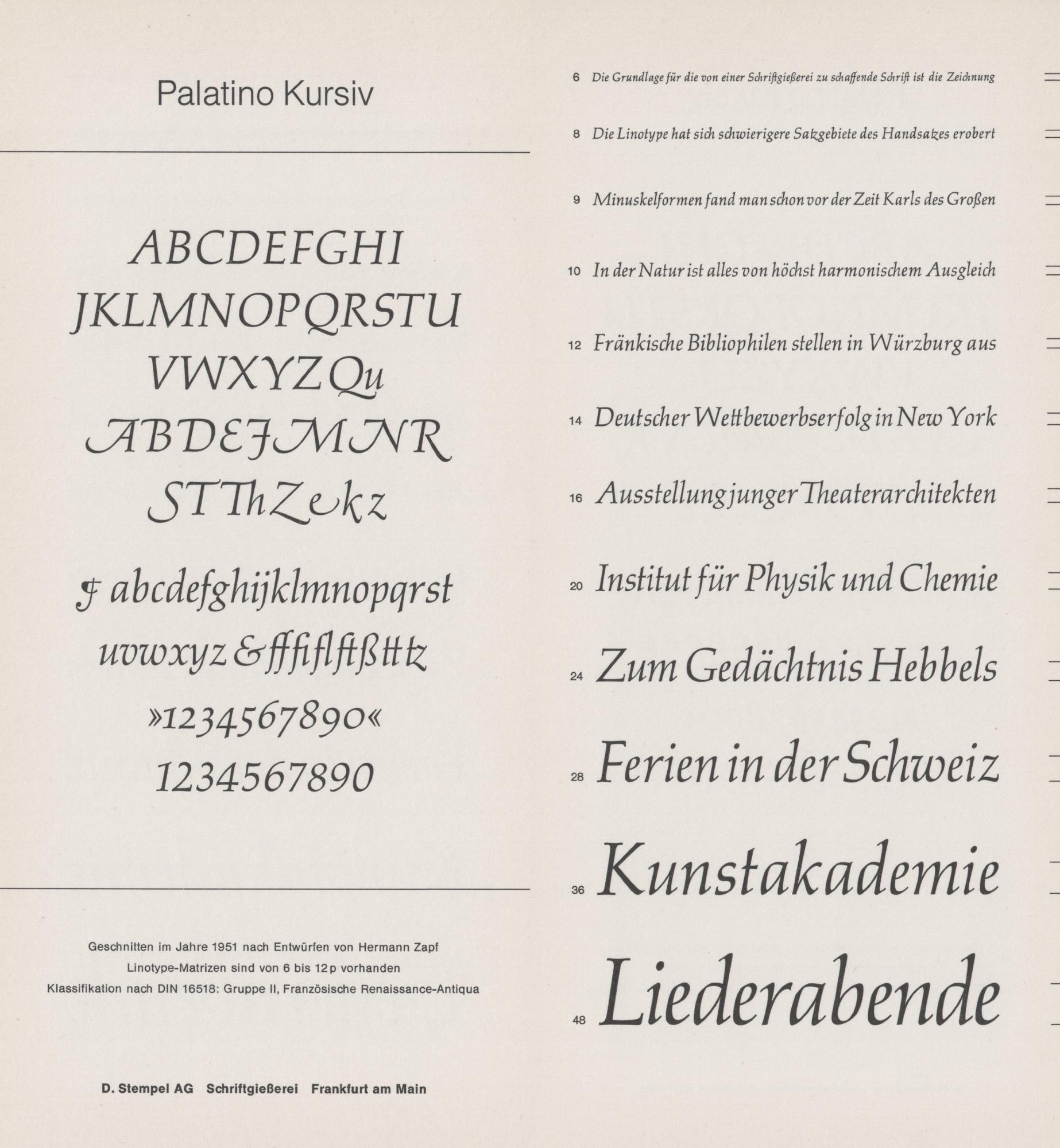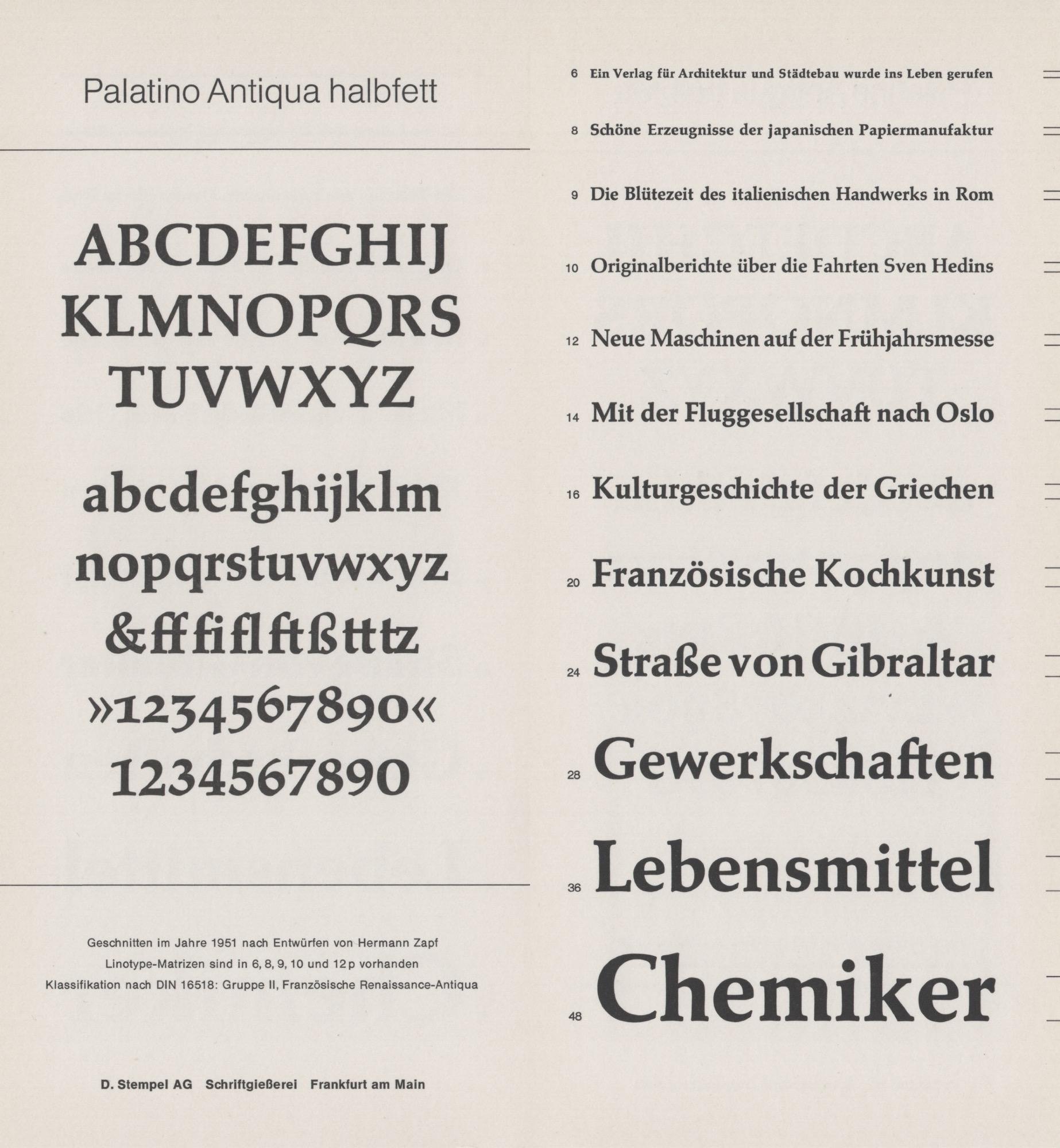
Die Palatino ist neben der Optima die bekannteste Schrift Hermann Zapfs. Seit ihrem Erscheinen zur Mitte des 20. Jahrhunderts findet sie sich in regelmäßiger Anwendung. Benannt ist die Schrift nach dem Italiener Giovanbattista Palatino, einem Schreibmeister des 16. Jahrhunderts und Zeitgenossen von Michelangelo und Claude Garamond.
»Hermann Zapf wies mit dieser Schrift überzeugend nach, daß auf den Grundlagen der Renaissance immer noch weitergebaut werden kann, daß es hier immer noch genügend Möglichkeiten zum Variieren verschiedener Details der Schriftzeichnung gibt, durch die die Individualität der eigenen Auffassung ausgedrückt werden kann« heißt es in Die schöne Schrift von František Muzika
Korrekturphasen der Palatino Kursiv (hier noch unter dem später verworfenen Namen Medici)
Zapf baut seine Palatino auf antike Proportionen auf und haucht ihnen dabei kalligrafischen Charakter ein. Die Schrift läuft vergleichsweise weit. Dies macht die Schrift jedoch auch besonders robust und lesefreundlich.
Buchstabenbelegung in der Bleisatzversion von 1950
Der erste Druck in einem Probegrad erfolgt 1949 in dem Buch »Von der dreifachen Ehrfurcht, Gedanken Goethes über Erziehung zu edlem Menschentum« als Privatdruck der Schriftgießerei D. Stempel. Die Schrift erscheint dann 1950 für Hand- und Linotypesatz.
Eine leichtere Version der Palatino wurde von Linotype unter der Bezeichnung Aldus Antiqua herausgebracht. Zugehörig waren ebenfalls die Versal-Alphabete Michelangelo, Sinista und Phidias.
Die Palatino Nova (2005) ist eine moderne Überarbeitung für den Digitalsatz durch Akira Kobayashi. Die neue Version vermeidet die Einschränkungen von Blei- und Fotosatz und ist auch im Zeichenvorrat den heutigen Erfordernissen angepasst. Die Michelangelo heißt nun Palatino Nova Titling und die Sinista wurde in Palatina Nova Imperial umgetauft.
Mit der Palatino Sans bekam die Palatino im 2006 eine serifenlose Schwester.
2013 erschien zudem eine eText-Version in 4 Schnitten (normal, kursiv, fett, fett kursiv) speziell für den Einsatz auf elektronischen Lesegeräten. Die Überarbeitung erfolgte in diesem Fall von Toshi Omagari.